Ephemera Handwritten Script Wallpaper
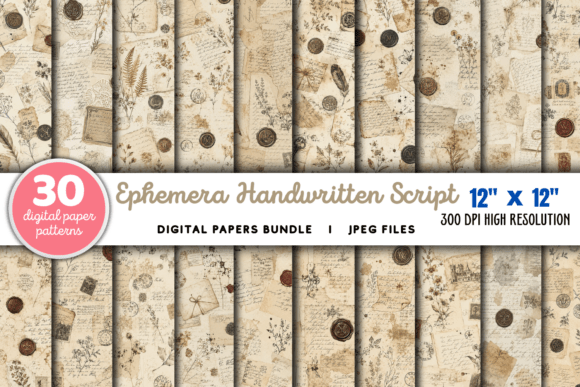
Ephemera Handwritten Script Wallpaperのような高品質の素材をお探しの場合、このプレミアムパッケージはクリエイティブなプロジェクトに素晴らしい選択です。
POD(オンデマンド印刷)製品、結婚式の招待状、またはソーシャルメディアのグラフィックを作成している場合でも、Ephemera Handwritten Script Wallpaperは理想的です。